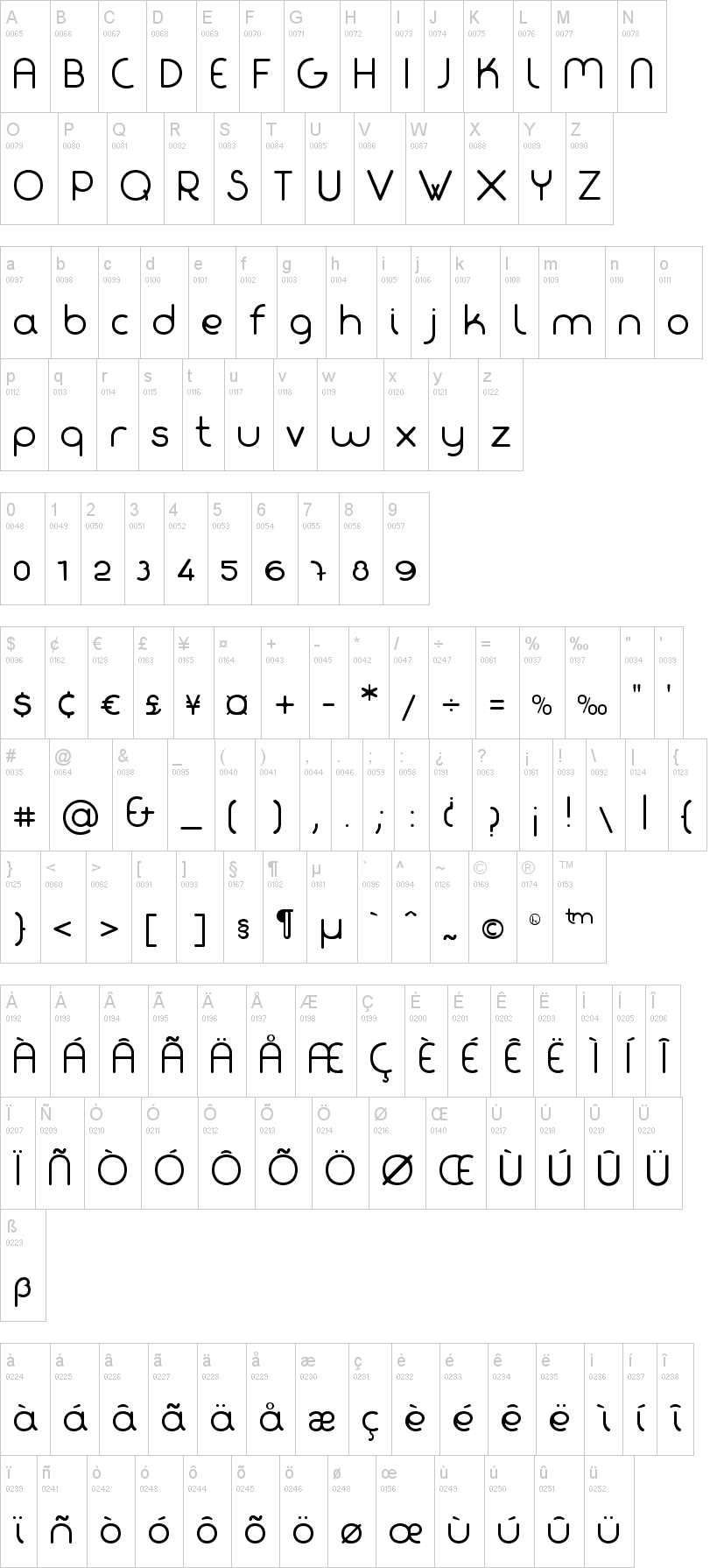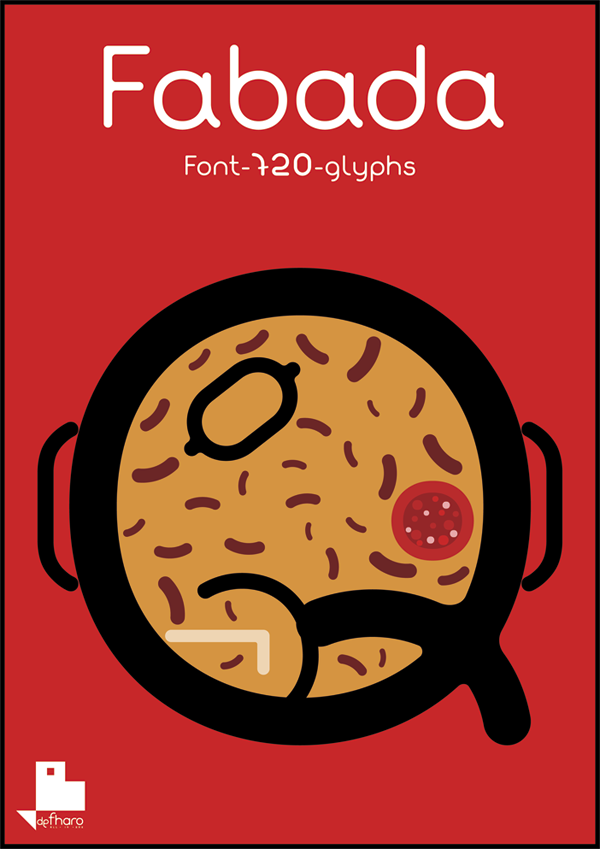
Шрифт Fabada
Soy deFharo, diseñador gráfico y web freelance y a este potaje de letras la he llamado: Fabada.
Fabada es una display retro font redondeada con 720 glifos, esta fuente fue con la que comencé a experimentar con el diseño tipográfico, después fue la génesis de mi otra tipografía llamada: La chata. Prueba a usar las funciones Opentype.